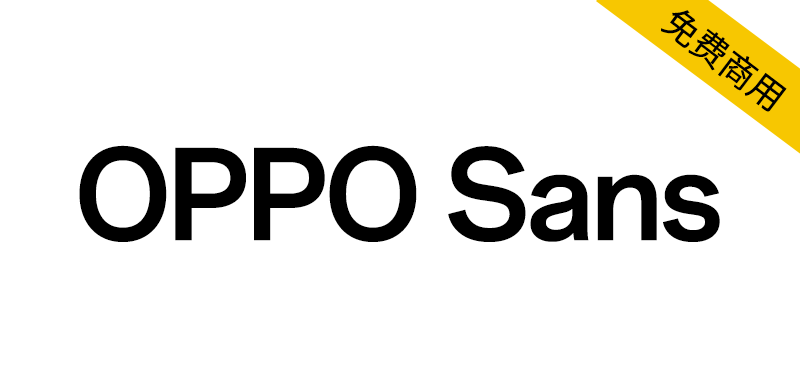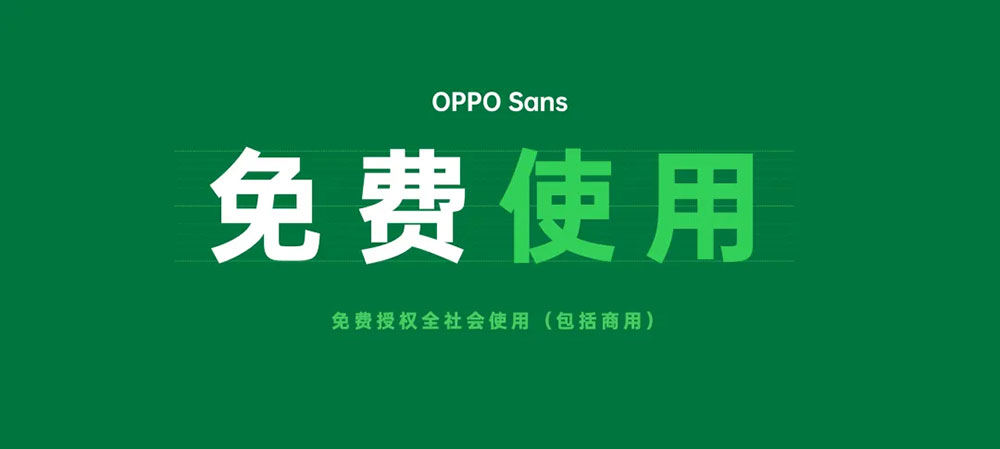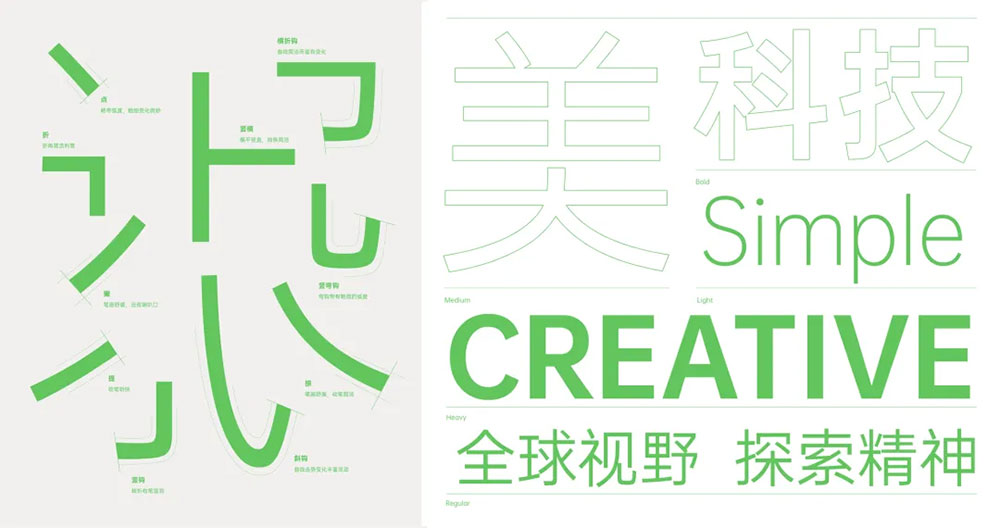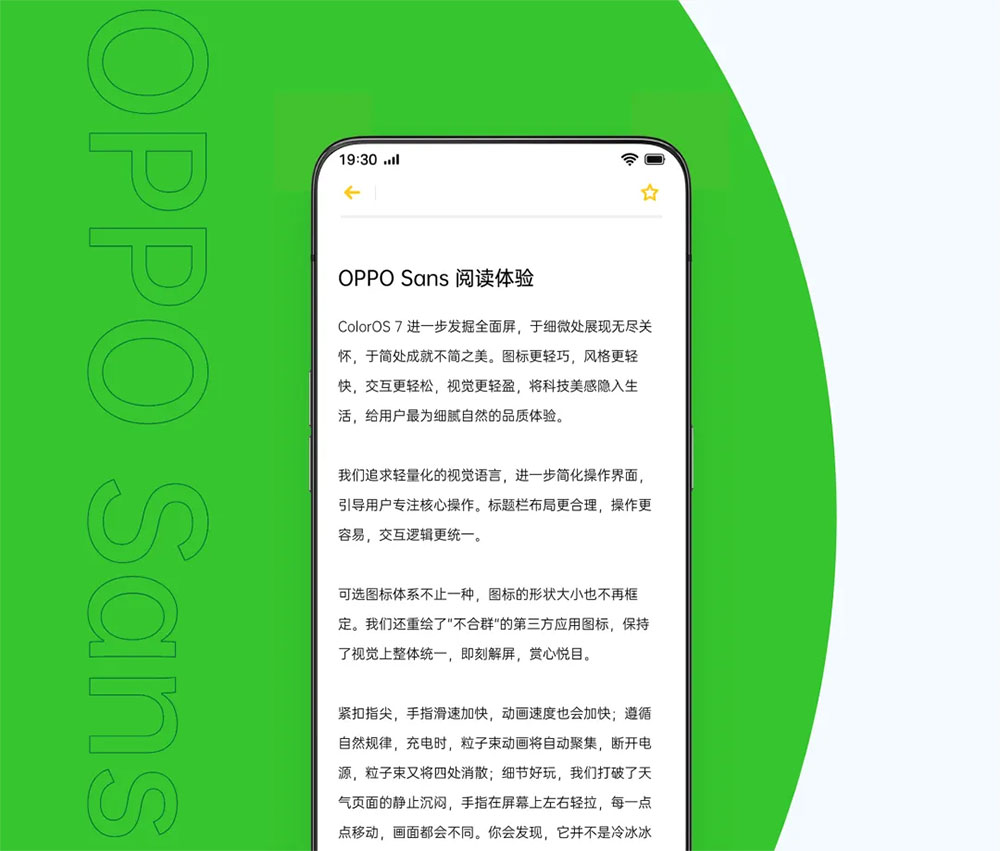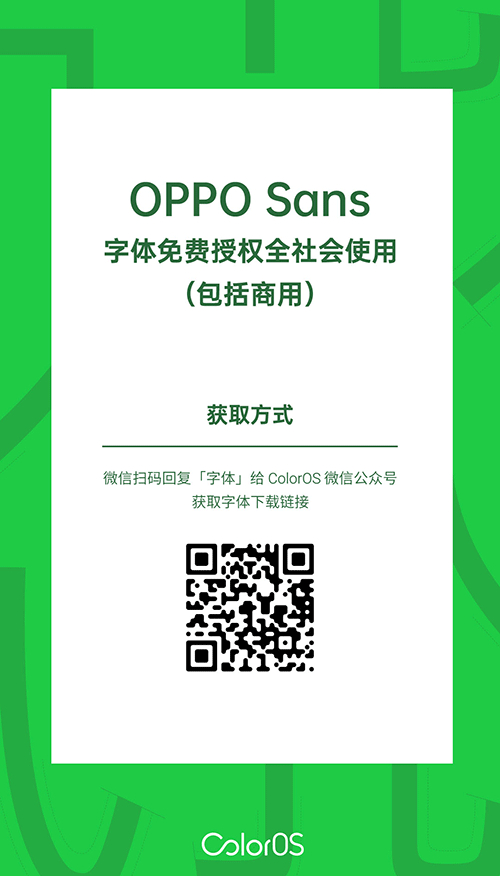
OPPO Sans 自 2019 年发布以来,已获得大量行业与用户的积极评价。为了给用户带来更舒适的屏幕阅读体验,OPPO Sans 4.0 融合了用于阅读的 Text 字体和用于展示的 Display 字体的特征,这样既秉承过往稳定舒展的字形便于阅读,又进一步提升了字体的表现力。
在 OPPO Sans 3.0 基础上,OPPO Sans 4.0 优化了字符曲线和增加字体特性。尤其对数字和字母进行精心打磨,这样能在如锁屏时间、桌面插件、时钟字体以及一些大号的数据字体表达上更具表现力,如大字号字体采用精致的曲线,自然的弧线,字母造型更加圆润饱满,让字符特点更加鲜明,表现力更佳,进一步提升视觉美感。
OPPO Sans 4.0 在大中小不同字体下采用不同的设计,大字号侧重表现力的塑造,中字号注重阅读体验的舒适,小字号注重基础的可读性和识别性,部分字符采用更简洁的造型及更具辨识度的轮廓,并拥有更加宽松的字间距,满足不同字体应用需求,增强字体清晰度和易读性。
同时,OPPO Sans 4.0 还支持 Opentype 字体特性,在文本排列组合时能够自动响应文本规则,让字体排版更加精致,符合实际设计、开发需求,如:数字和拉丁字母之间的冒号可自动居中显示,数字单位角标可上标和下标展示,可根据使用场景切换数字的变宽/等宽样式,大写括号形态,将分数格式文本转换成更直观的视觉样式等,由此带来更加自然的阅读体验。
针对高分辨率屏幕的显示特性,通过减小字锋、去出脚、均匀布白等方式,进一步提升整洁度与通透感,展现优雅、挺拔、充满生命力的品牌气质,在亲和中透露出 OPPO 的现代科技美感。